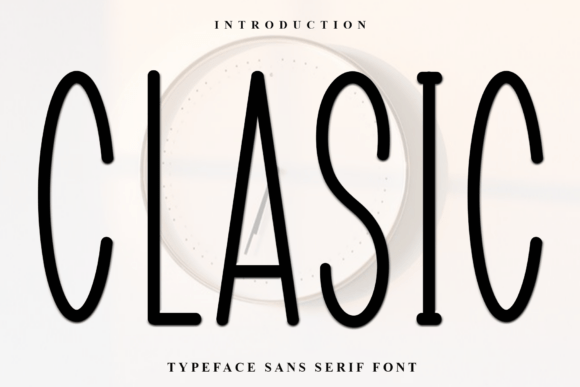
Clasic
Ulasan Lengkap Font “Clasic”: Pilihan Terbaik untuk Desain Santai dan Kreatif
Jika Anda sedang mencari tipografi yang memancarkan kehangatan, keceriaan, dan kesan hand‑drawn, Clasic adalah jawabannya. Font ini dirancang khusus untuk memberi nuansa ramah dan bersahabat pada setiap proyek, mulai dari undangan pribadi hingga grafis media sosial. Berikut ulasan detail yang akan membantu Anda memahami keunggulan dan kegunaan Clasic.
- Gaya dan Karakter: Garis‑garis melengkung yang lembut serta stroke yang playful menciptakan tampilan yang santai dan mudah didekati. Cocok untuk brand yang ingin menampilkan sisi humanis dan approachable.
- Keunikan Hand‑Drawn: Setiap huruf tampak seolah‑olah digambar tangan, menambah sentuhan personal dan unik pada desain Anda.
- Fleksibilitas Penggunaan: Ideal untuk proyek pribadi, undangan pernikahan, kartu ucapan, poster acara, dan konten visual di Instagram, TikTok, atau Facebook.
- Kompatibilitas Bahasa: Menyediakan karakter lengkap untuk bahasa Portugis, sehingga tidak ada masalah dengan aksen atau tanda diakritik.